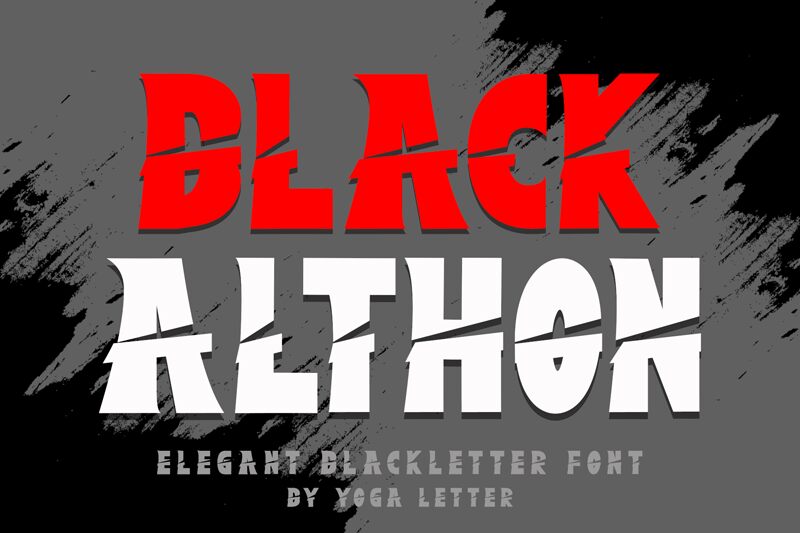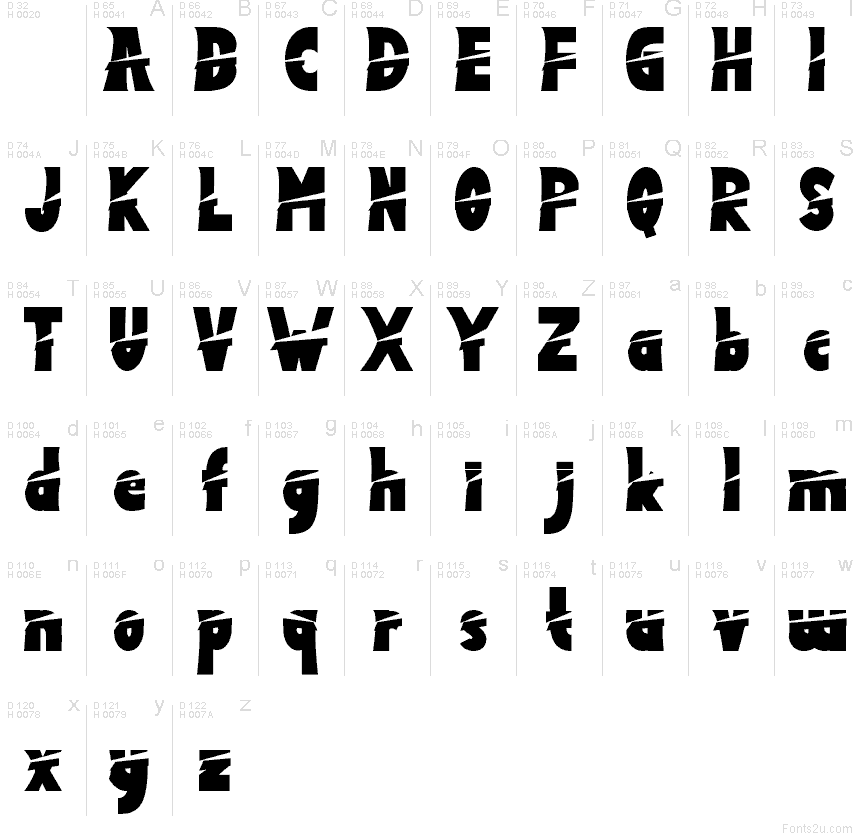
Black Althon Demo
Black Althon de Yoga Letter es una tipografía display gratuita y distorsionada con una estructura de corte tipo cómic, donde cada forma redondeada parece haber sido rebanada y desplazada en cortes horizontales afilados. Las letras mantienen un contorno grueso y redondeado, pero las constantes incisiones y uniones irregulares le otorgan un ritmo inquieto y fragmentado.
Black Althon funciona muy bien en titulares de carteles, gráficos para juegos, portadas de estilo cómic, diseño musical y banners llamativos para redes sociales. Esta fuente gratuita aporta la distorsión necesaria para textos cortos que buscan impactar, mientras que su base redondeada permite usarla en logotipos, flyers de eventos y palabras con énfasis que requieran un estilo agrietado y hecho a mano.